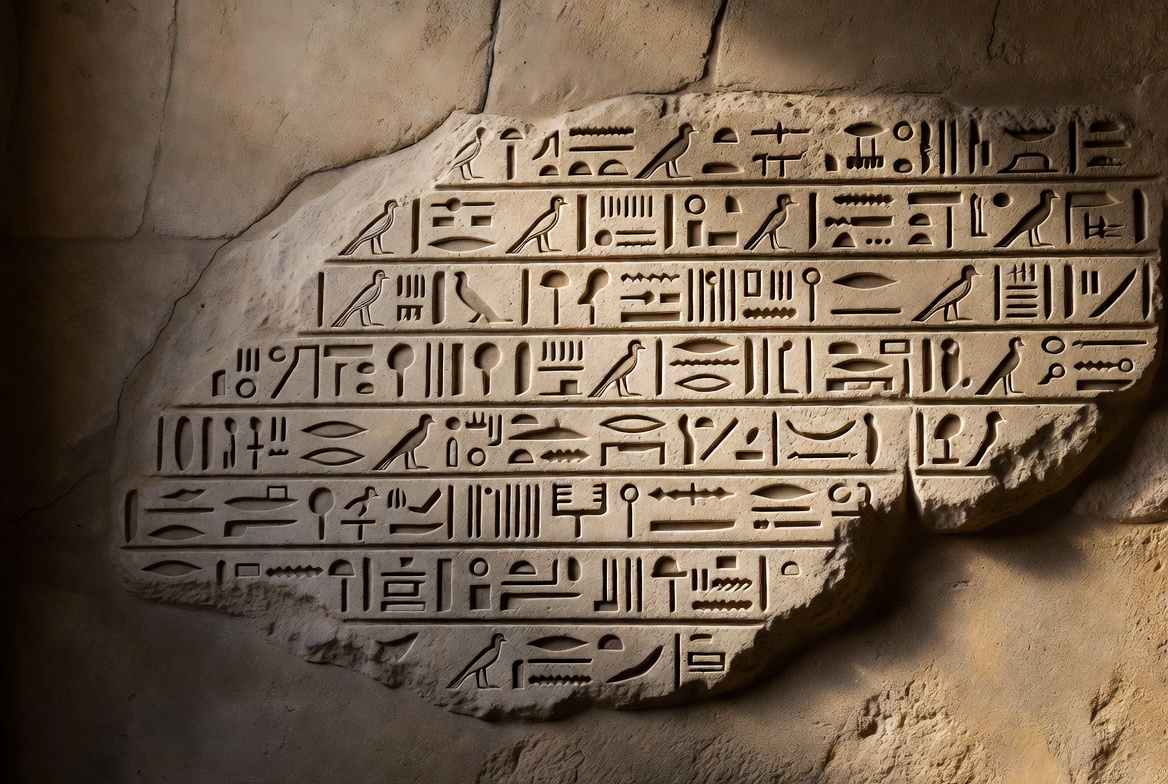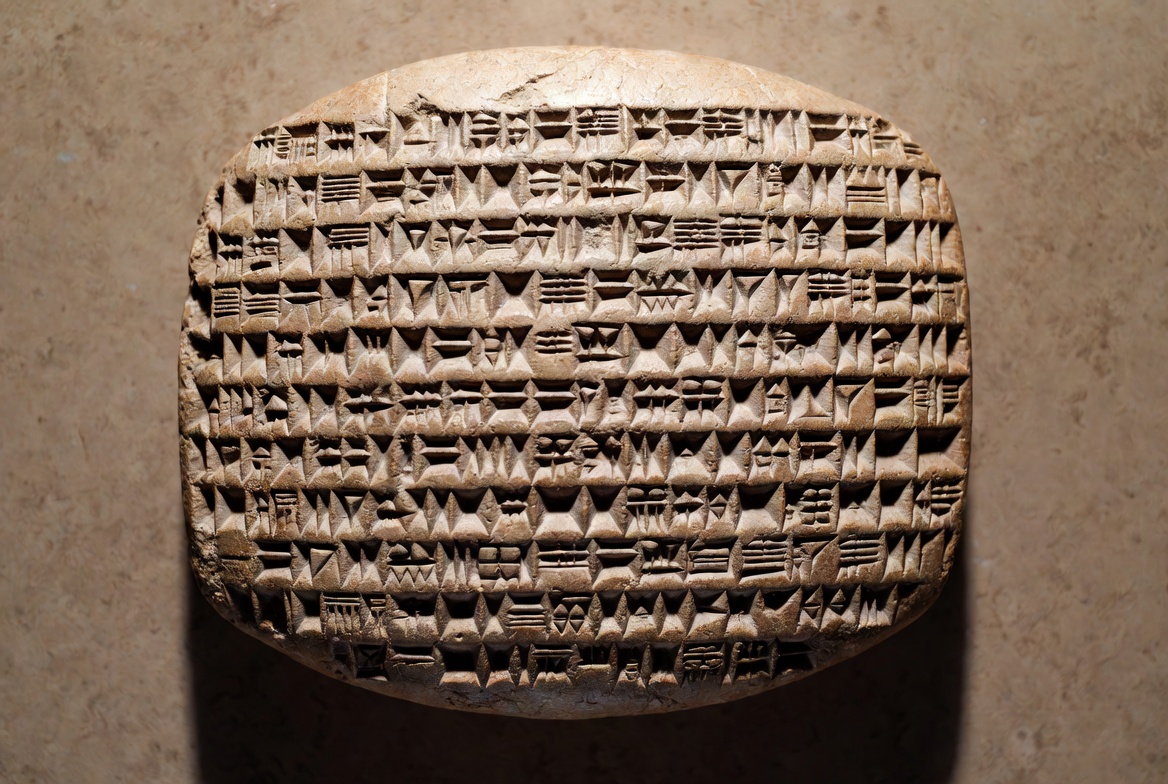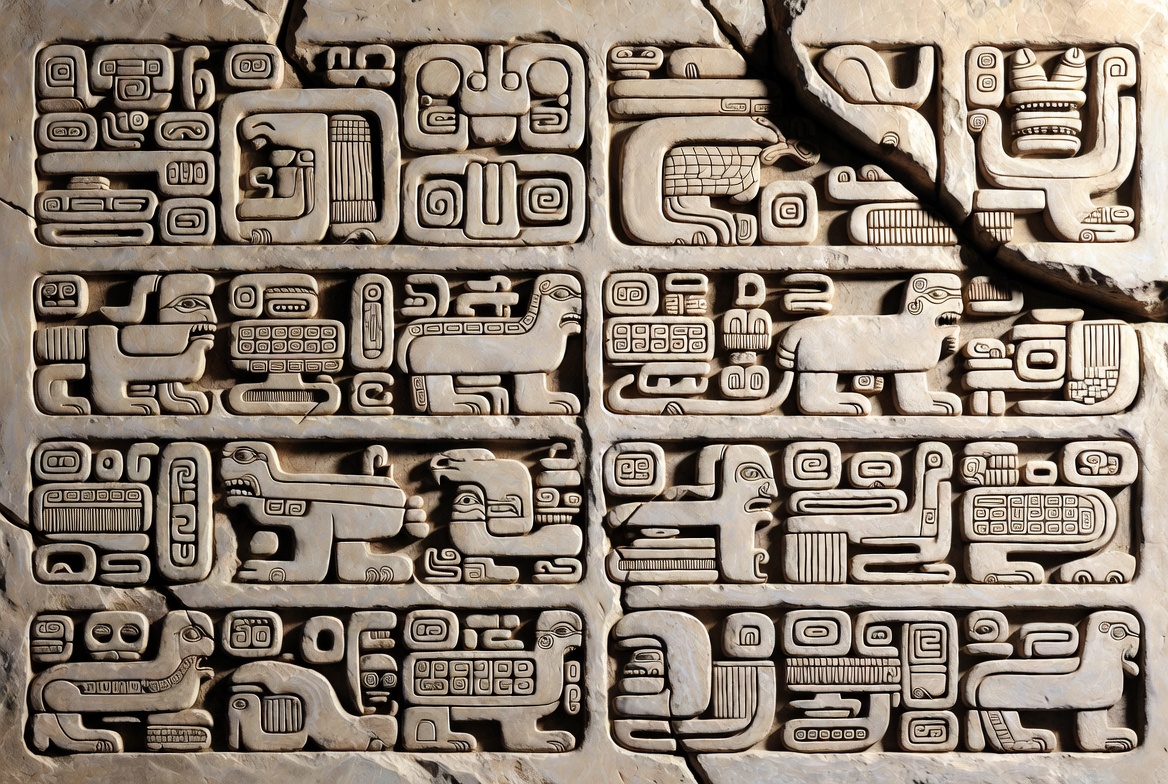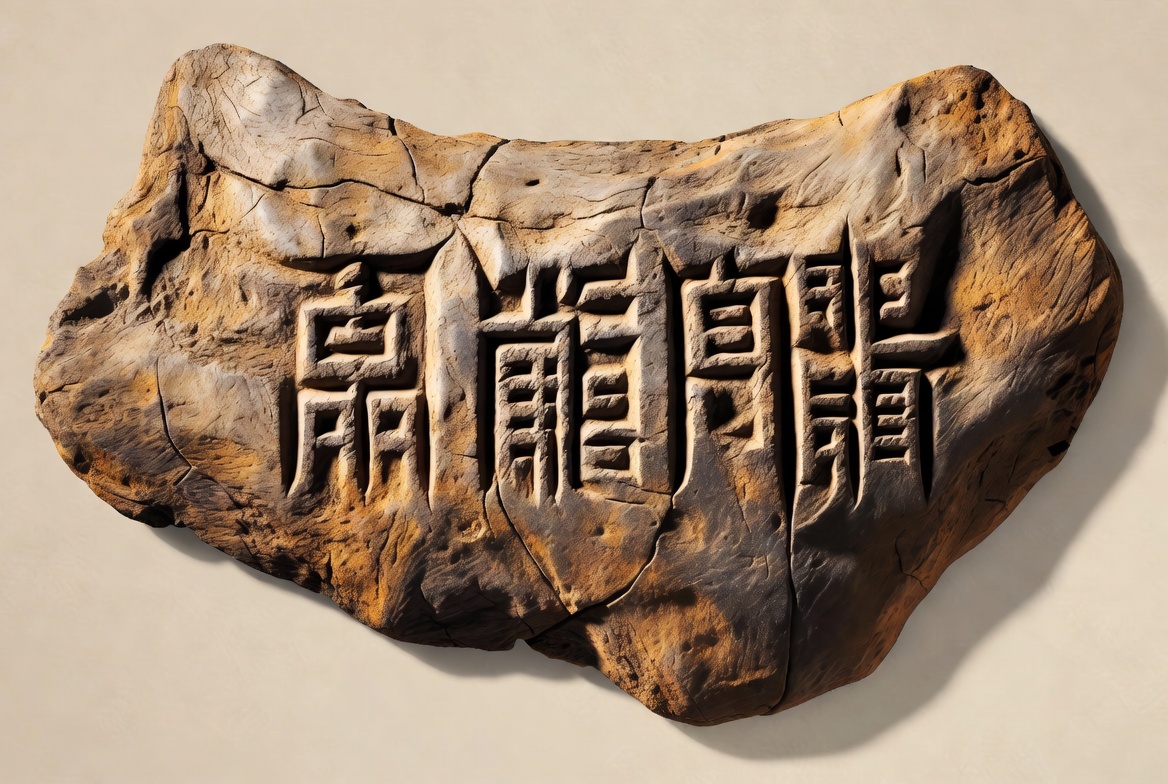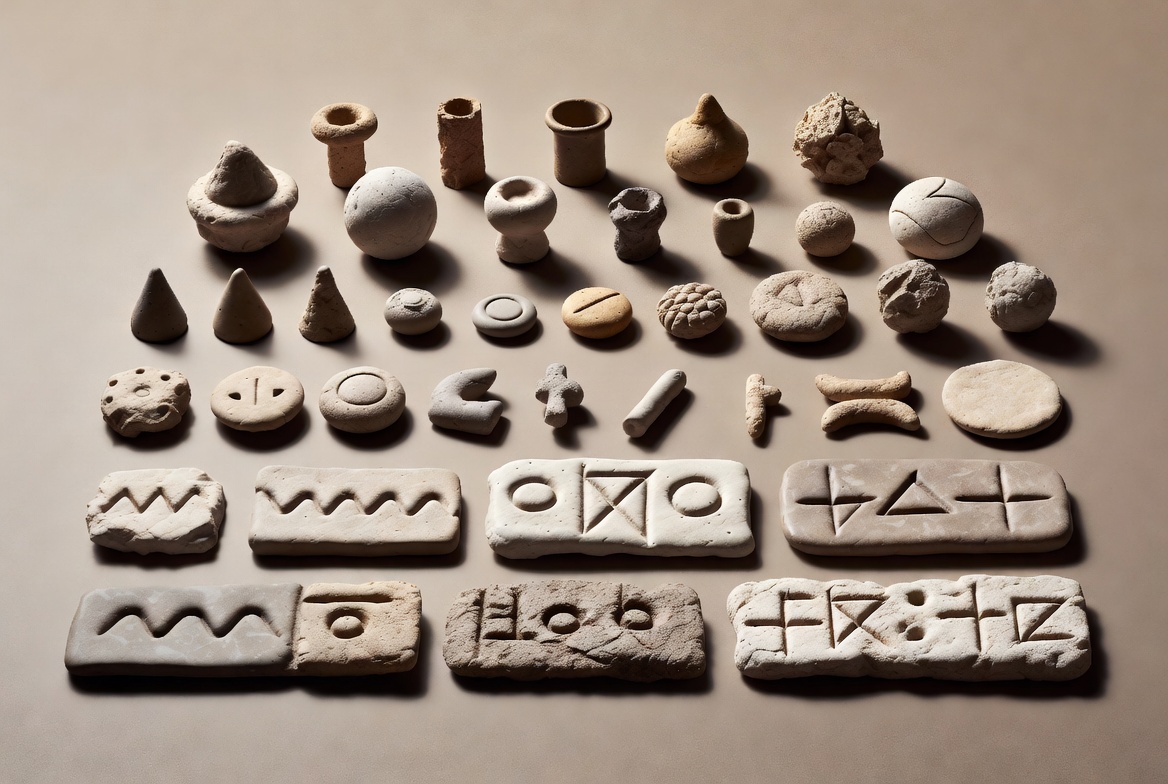
Geschichte der Schrift – Teil 1: Die Anfänge
Wann und wo entstand die erste Schrift? Ein Blick auf die Anfänge der Schrift in Mesopotamien und Ägypten.
Die Schrift gehört zu den wichtigsten Erfindungen der Menschheit. Sie ermöglicht es, Wissen über Generationen hinweg zu speichern, Verträge festzuhalten und komplexe Gesellschaften zu organisieren. Doch wann und wo wurde zum ersten Mal wirklich geschrieben?
Die Antwort ist weniger eindeutig, als man denken könnte – und genau das macht die Geschichte der Schrift so spannend.
Proto-Schrift und echte Schrift
Bevor es eine echte Schrift gab, nutzten Menschen bereits seit Jahrtausenden Zeichen und Symbole. Archäologen sprechen hier von Proto-Schrift. Dazu gehören zum Beispiel Kerbhölzer, Zählmarken aus Ton oder einfache Bildzeichen. Diese Systeme konnten Mengen oder Gegenstände darstellen, aber noch keine gesprochene Sprache wiedergeben.
Illustration einer Proto-Schrift: Frühe Zählmarken und einfache Bildzeichen
Von einer echten Schrift spricht man erst dann, wenn ein Schriftsystem in der Lage ist, eine Sprache weitgehend vollständig abzubilden – also Wörter, Laute oder grammatische Strukturen festzuhalten.
Die älteste bekannte Schrift: Mesopotamien
Nach heutigem Forschungsstand entstand die älteste gut belegte Schrift im südlichen Mesopotamien, im Gebiet des heutigen Irak. Dort entwickelten die Sumerer in der Stadt Uruk um etwa 3400–3200 v. Chr. ein Schriftsystem, aus dem später die berühmte Keilschrift hervorging.
Die frühesten Tontafeln dienten vor allem der Verwaltung: Sie dokumentierten Getreidelieferungen, Viehbestände und Abgaben. Die Schrift entstand also nicht aus literarischem Bedürfnis, sondern aus praktischen Gründen – vor allem aus der Notwendigkeit, wirtschaftliche Vorgänge in wachsenden Stadtstaaten zuverlässig festzuhalten.
Illustration einer sumerischen Keilschrift-Tontafel aus Mesopotamien
Die Keilschrift wurde zunächst mit einem Schilfrohrgriffel in feuchten Ton gedrückt. Die charakteristische keilförmige Form der Zeichen gab dem Schriftsystem später seinen Namen.
Parallelentwicklung in Ägypten
Fast zur gleichen Zeit – etwa ab 3250–3200 v. Chr. – erscheinen in Ägypten die ersten Hieroglyphen. Ob die ägyptische Schrift unabhängig entstanden ist oder durch Kontakte mit Mesopotamien beeinflusst wurde, ist in der Forschung bis heute umstritten. Klar ist jedoch: Auch in Ägypten diente die Schrift zunächst vor allem administrativen und repräsentativen Zwecken.
Illustration ägyptischer Hieroglyphen
Schrift wurde mehrfach erfunden
Lange ging man davon aus, dass die Schrift nur einmal erfunden und dann in andere Kulturen weitergegeben wurde. Heute geht die Mehrzahl der Forscher davon aus, dass echte Schriftsysteme mehrfach unabhängig entstanden sind – mindestens in:
- Mesopotamien (Keilschrift)
- Ägypten (Hieroglyphen)
- China (Orakelknochen-Schrift)
Illustration einer chinesischen Orakelknochen-Schrift
- Mesoamerika (u. a. Maya-Schrift)
Illustration der Maya-Schrift aus Mesoamerika
Die sumerische Keilschrift bleibt jedoch das älteste weitgehend gesicherte Beispiel einer echten Schrift.
Ausblick
Mit der Erfindung der Schrift begann eine neue Epoche der Menschheitsgeschichte. Aus einfachen Verwaltungszeichen entwickelten sich im Lauf der Jahrtausende Alphabete, Handschriften und schließlich die Typografie, wie wir sie heute kennen.